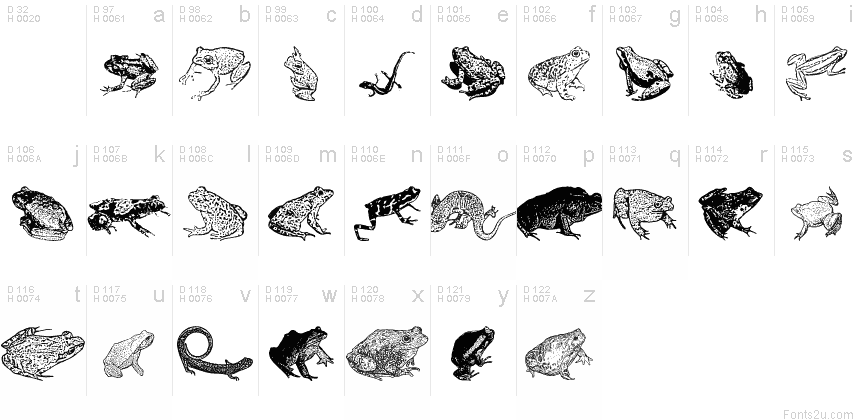
Amphibi Print od Astigmatic One Eye to darmowy krój typu dingbat, który zmienia każde naciśnięcie klawisza w bogato teksturowaną ilustrację żaby. Każda żaba wygląda jak narysowana ręcznie – od przyczajonych sylwetek po skaczące pozy – dzięki czemu projekty zyskują natychmiastowy, przyrodniczy charakter. W dużym rozmiarze kształty te mają wyrazisty, stemplowy wygląd, a po pomniejszeniu czytają się jak misterne, kolekcjonerskie ikony.
Używając Amphibi Print, wprowadzisz oryginalną, pełną natury energię do arkuszy z zadaniami dla dzieci, materiałów edukacyjnych, gadżetów do zoo czy akwariów, plakatów ekologicznych, naklejek oraz kreatywnego brandingu sklepów zoologicznych czy terrarystycznych. Ten darmowy font doskonale współpracuje z czystym, geometrycznym krojem bezszeryfowym w etykietach lub podpisach, dzięki czemu żaby pozostają na pierwszym planie, a tekst zachowuje czytelność i przejrzystość.